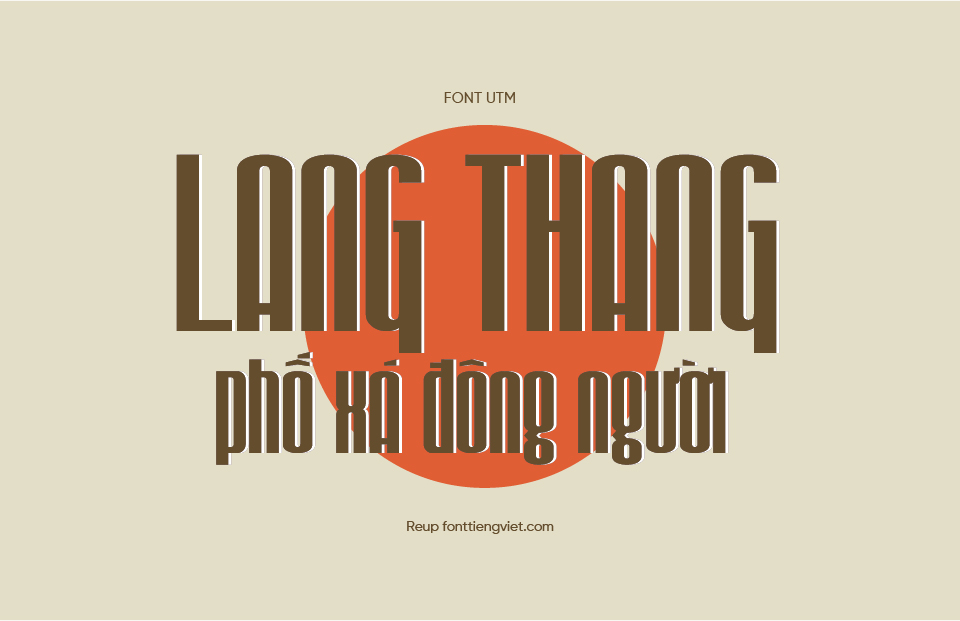
Trong thế giới thiết kế đồ họa, việc tìm kiếm một Font Chữ độc đáo, mạnh mẽ và đã được Việt hóa hoàn chỉnh luôn là ưu tiên hàng đầu. Và hôm nay, chúng tôi muốn giới thiệu đến bạn một “viên ngọc quý” đang rất được ưa chuộng: Font Việt hóa UTM Iron Gothic. Đây không chỉ là một phông chữ; nó là tuyên ngôn của sự cá tính, mang hơi thở mạnh mẽ của phong cách Industrial và Vintage. Đối với các bạn học sinh, sinh viên đang thực hiện các đồ án tốt nghiệp hay thiết kế ấn phẩm học đường, việc sở hữu bộ font này sẽ giúp tác phẩm của bạn nổi bật hơn bao giờ hết, tạo ra ấn tượng thị giác sâu sắc ngay từ cái nhìn đầu tiên. Hãy cùng khám phá chi tiết về bộ font tuyệt vời này và cách tải về miễn phí nhé.
Đặc Điểm Nổi Bật Của Font Việt hóa UTM Iron Gothic
Bộ font này được xây dựng dựa trên phong cách Gothic, nhưng được làm mềm mại và hiện đại hơn qua bàn tay của nhóm UTM, đồng thời được tối ưu hóa đầy đủ cho tiếng Việt. Sự “Iron” (sắt) trong tên gọi gợi lên cảm giác về sự vững chắc, công nghiệp, và một chút gì đó cổ điển, mạnh mẽ. Đây là lý do tại sao nó thường được sử dụng trong các thiết kế đòi hỏi độ tương phản cao và sự chú ý tức thì. Mỗi ký tự đều được chăm chút tỉ mỉ, đảm bảo tính thẩm mỹ cao dù bạn sử dụng nó cho tiêu đề lớn hay các chi tiết nhỏ trong thiết kế của mình.
Khả năng Việt hóa hoàn chỉnh là một yếu tố then chốt giúp Font Việt hóa UTM Iron Gothic trở thành lựa chọn lý tưởng tại Việt Nam. Nó hỗ trợ đầy đủ các dấu câu, dấu thanh (sắc, huyền, hỏi, ngã, nặng), và các ký tự đặc biệt cần thiết cho ngôn ngữ tiếng Việt. Điều này đặc biệt quan trọng khi bạn cần in ấn các tài liệu học tập, báo cáo chuyên đề hoặc các ấn phẩm truyền thông cho trường học, đảm bảo không xảy ra lỗi hiển thị hoặc thiếu sót ký tự nào.
Thiết Kế Độc Đáo – Phù Hợp Với Xu Hướng Typography Hiện Đại
Trong bối cảnh các trường học và tổ chức giáo dục ngày càng chú trọng đến thương hiệu và truyền thông, việc sử dụng các kiểu chữ độc đáo như UTM Iron Gothic giúp nâng tầm chất lượng hình ảnh. Nó mang lại cảm giác chuyên nghiệp, lịch sự nhưng không kém phần sáng tạo. Các bạn sinh viên ngành Thiết kế đồ họa hay Truyền thông đa phương tiện thường xuyên chọn bộ font này để tạo điểm nhấn cho portfolio hoặc poster quảng bá sự kiện.
Đây là một trong những bộ font hiếm hoi có thể kết hợp hài hòa giữa tính cổ điển (Gothic) và sự năng động, hiện đại, rất được giới mộ điệu typography đánh giá cao.
Tại Sao Học Sinh, Sinh Viên Nên Ưu Tiên Sử Dụng Font UTM Iron Gothic?
Thời điểm chuẩn bị cho các kỳ thi tốt nghiệp, đồ án cuối khóa hay báo cáo thực tập là lúc các bạn trẻ cần những công cụ hỗ trợ tốt nhất để trình bày ý tưởng một cách chuyên nghiệp. Font Việt hóa UTM Iron Gothic chính là công cụ đó. Nó không chỉ đơn thuần là văn bản mà còn là yếu tố truyền tải cảm xúc và thông điệp một cách hiệu quả.
Các ứng dụng thực tế mà sinh viên có thể tận dụng font này:
- Bìa Đồ Án Tốt Nghiệp: Tạo tiêu đề đồ án (thesis title) ấn tượng, chuyên nghiệp, thể hiện sự nghiêm túc và đầu tư vào sản phẩm cuối cùng.
- Thiết Kế Ấn Phẩm Kỷ Yếu (Yearbook): Sử dụng cho các tiêu đề lớn, tên chuyên mục để tạo phong cách vintage, học đường độc đáo.
- Poster và Banner Sự Kiện: Thích hợp cho các sự kiện học thuật, workshop hoặc hoạt động ngoại khóa cần sự mạnh mẽ và rõ ràng.
- Slide Thuyết Trình Chuyên Đề: Dùng cho tiêu đề slide, thu hút sự chú ý của người nghe ngay lập tức, đặc biệt trong các môn học về kỹ thuật hoặc nghệ thuật.
Sự rõ ràng và tính thẩm mỹ cao của bộ font này giúp cải thiện trải nghiệm đọc, đặc biệt quan trọng khi trình bày các nội dung phức tạp hoặc các báo cáo khoa học dài hơi. Việc sử dụng font chữ đẹp và dễ đọc giúp tăng điểm ấn tượng cho người chấm bài hoặc giáo viên hướng dẫn của bạn.
Hãy lưu ý rằng việc sử dụng các font đã được Việt hóa giúp bạn tiết kiệm thời gian chỉnh sửa lỗi font và tập trung hoàn toàn vào nội dung sáng tạo của mình. Đây là một lợi thế không nhỏ khi các deadline đồ án sắp đến gần.
Tóm lại, Font Việt hóa UTM Iron Gothic là một tài nguyên quý giá không thể thiếu trong bộ sưu tập của bất kỳ nhà thiết kế nào, đặc biệt là các bạn học sinh, sinh viên đang tìm kiếm sự khác biệt. Với phong cách mạnh mẽ, độc đáo cùng khả năng hỗ trợ tiếng Việt hoàn hảo, nó sẽ là trợ thủ đắc lực giúp bạn tạo ra các ấn phẩm chất lượng cao, từ bài luận tốt nghiệp cho đến các thiết kế truyền thông ấn tượng. Đừng chần chừ, hãy tải về và trải nghiệm ngay sự khác biệt mà bộ Font Chữ này mang lại. Chúc bạn thành công với các dự án sáng tạo sắp tới!